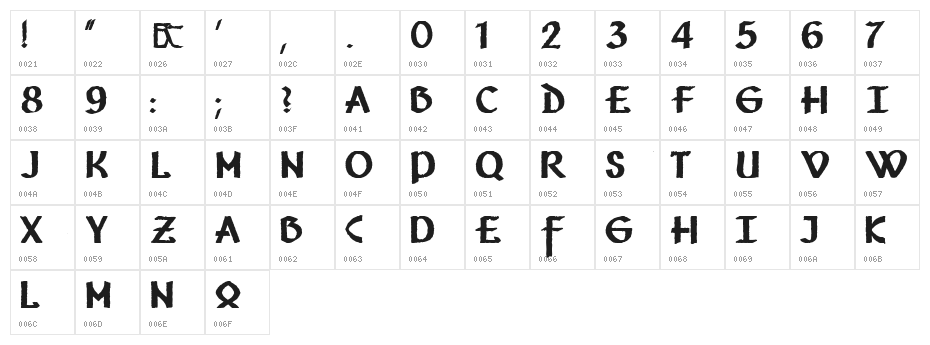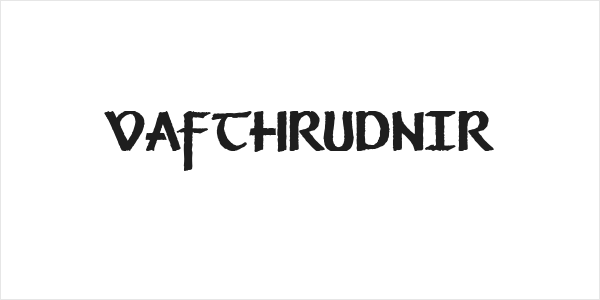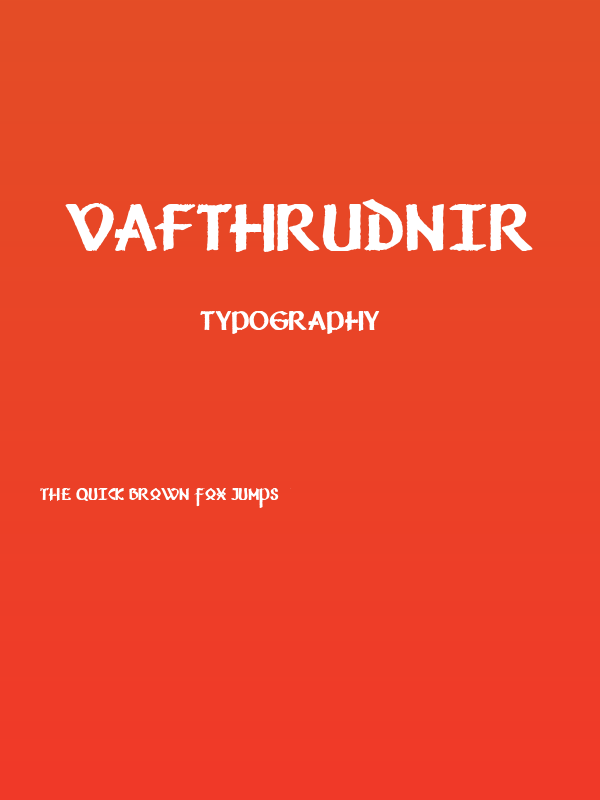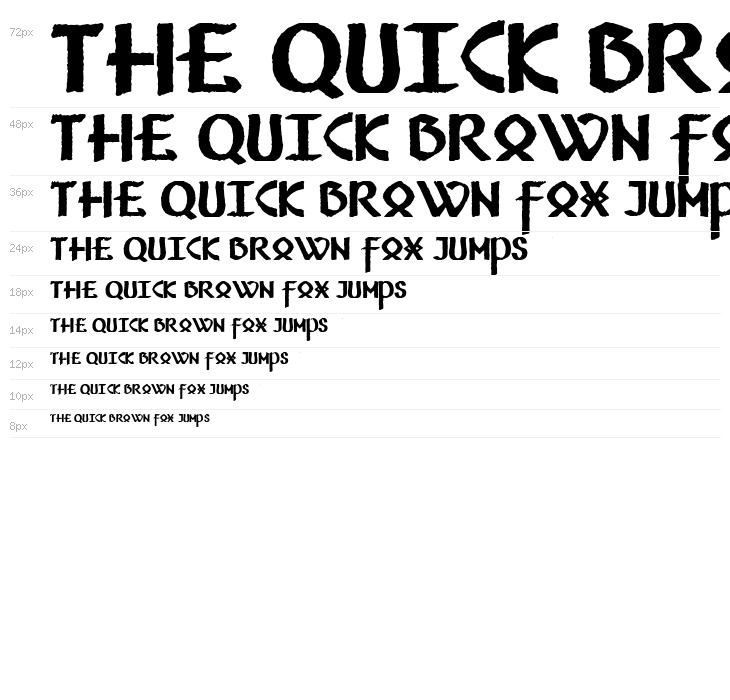
Vafthrudnir Font
| श्रेणियाँ | Gothic |
| कंट्रास्ट | High |
| समग्र शैली | Vintage |
| उपयोग का मामला | Logos, Headlines, Posters |
| सुझाए गए प्रोजेक्ट | Ideal for projects requiring a historical or fantasy theme, such as book covers, game titles, or themed event posters. |